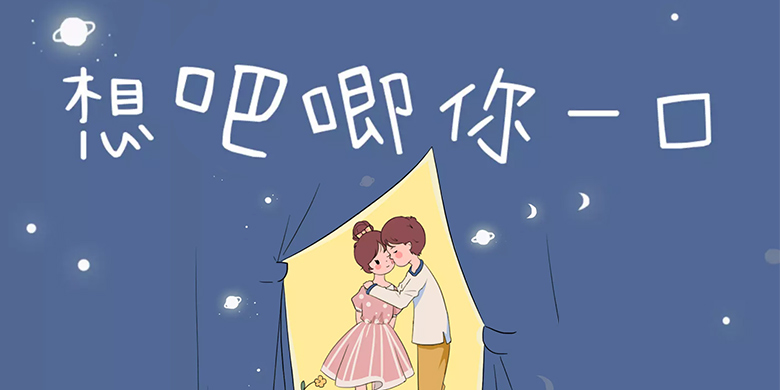
品牌:方正手迹设计师:俞亦婷发行时间:2019字库编码:大陆简体(GB2312-80)分类:创意书写字体属性:精品字
想吧唧你一口是一款趣味十足的字体,笔画方面,多用直线,极少有曲线,笔画走势收敛。结构方面多样变化,高低胖瘦不一。适用于少儿类书刊,及现代诗歌、短文的排版以及文化、商业类品牌的广告语设计。